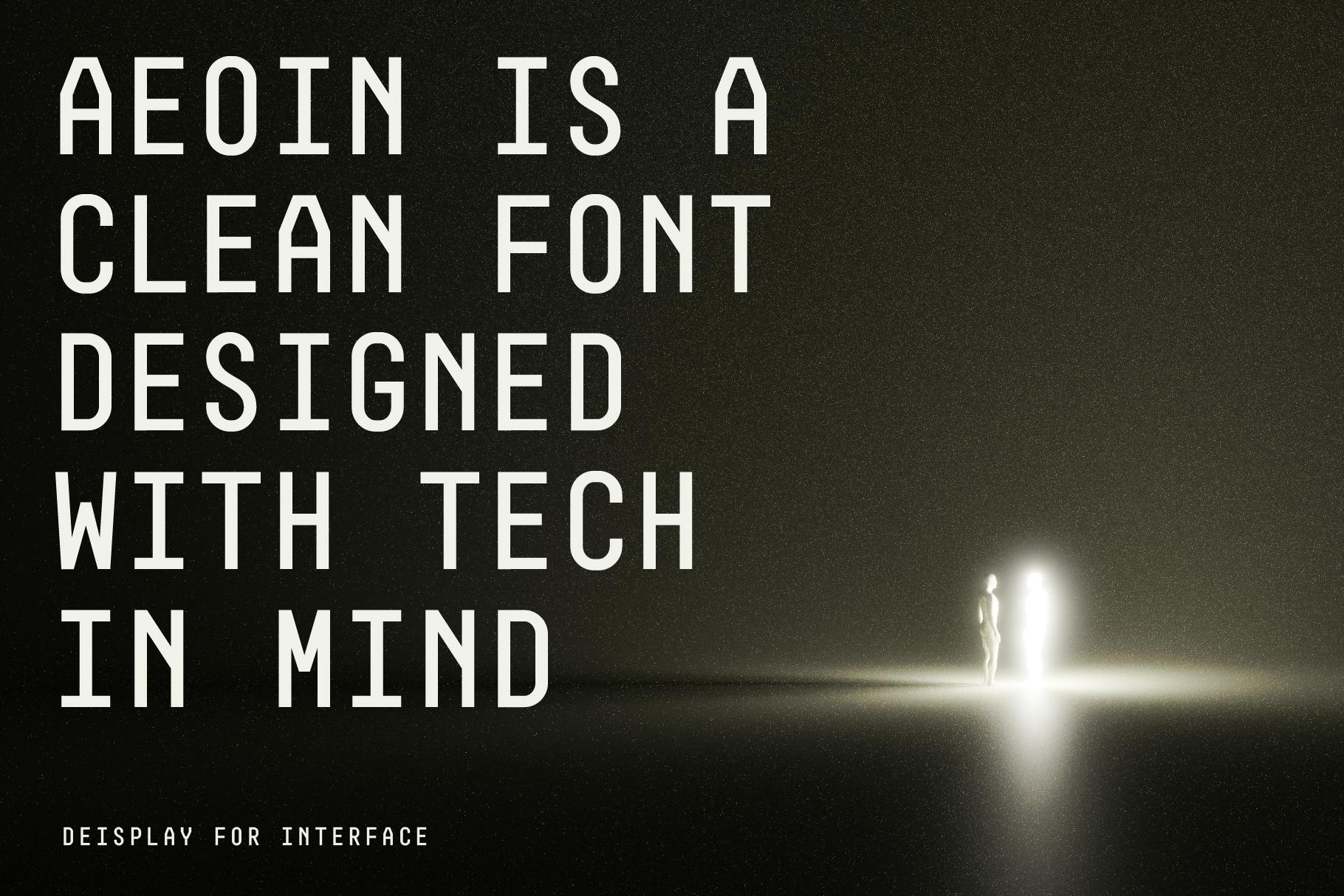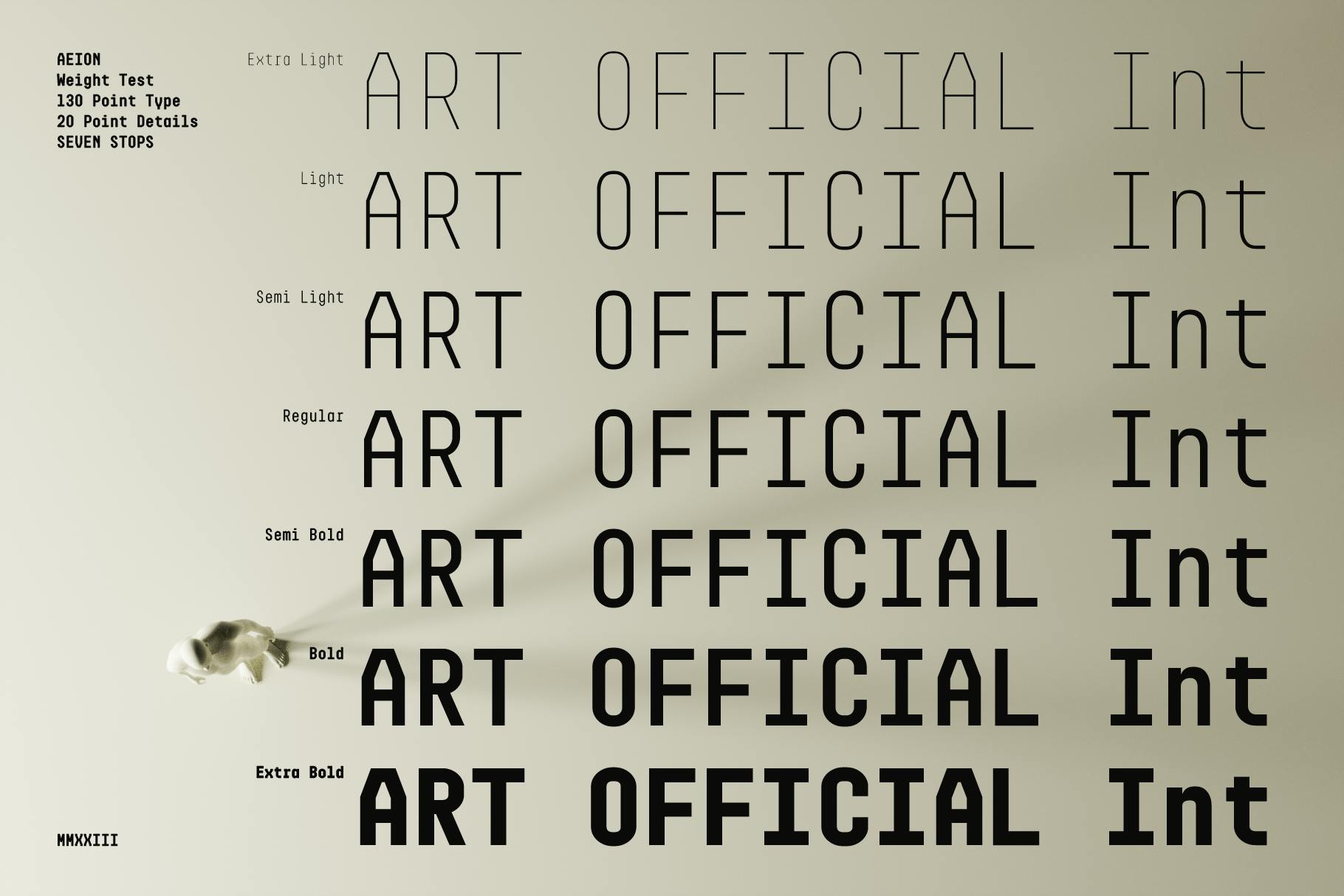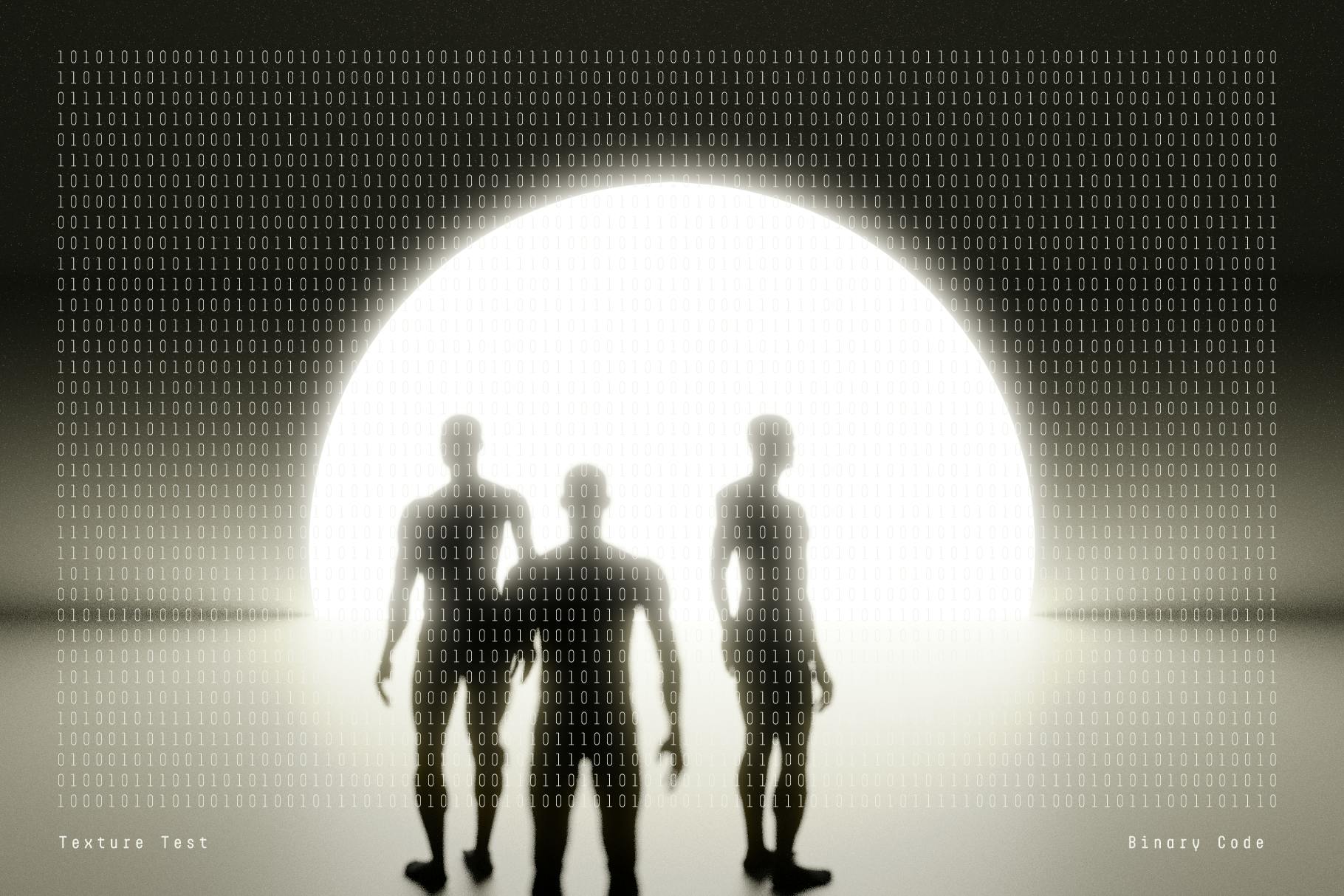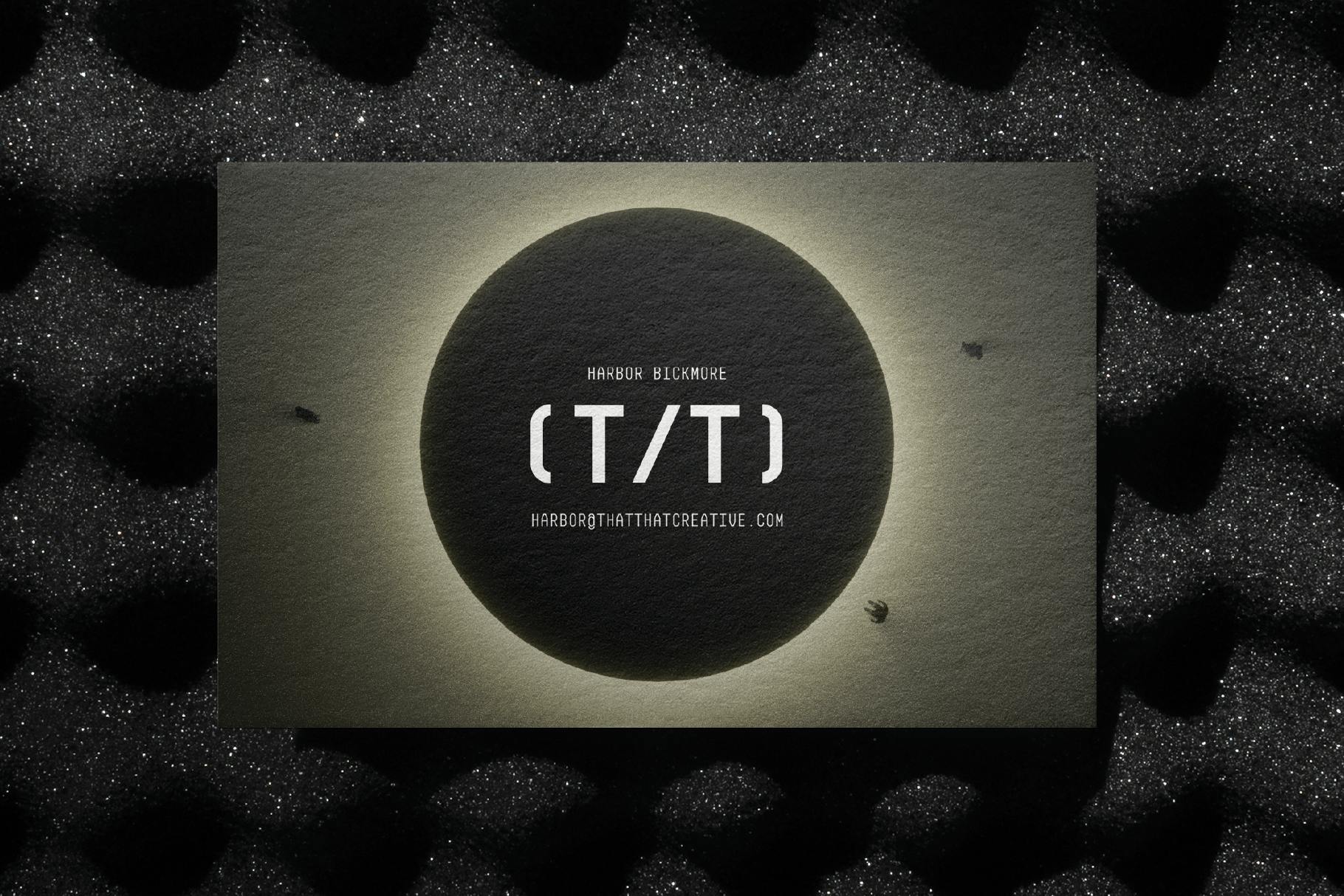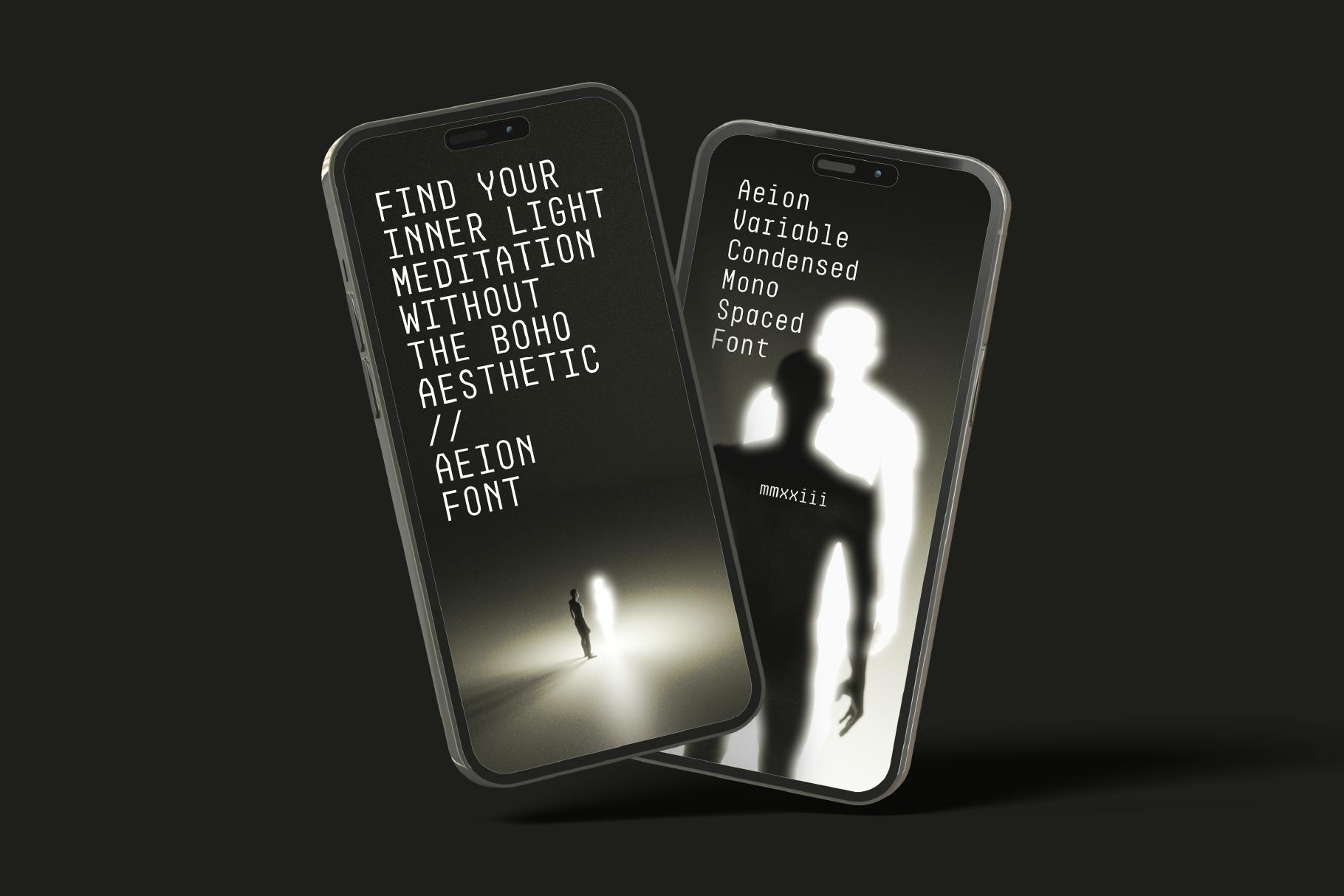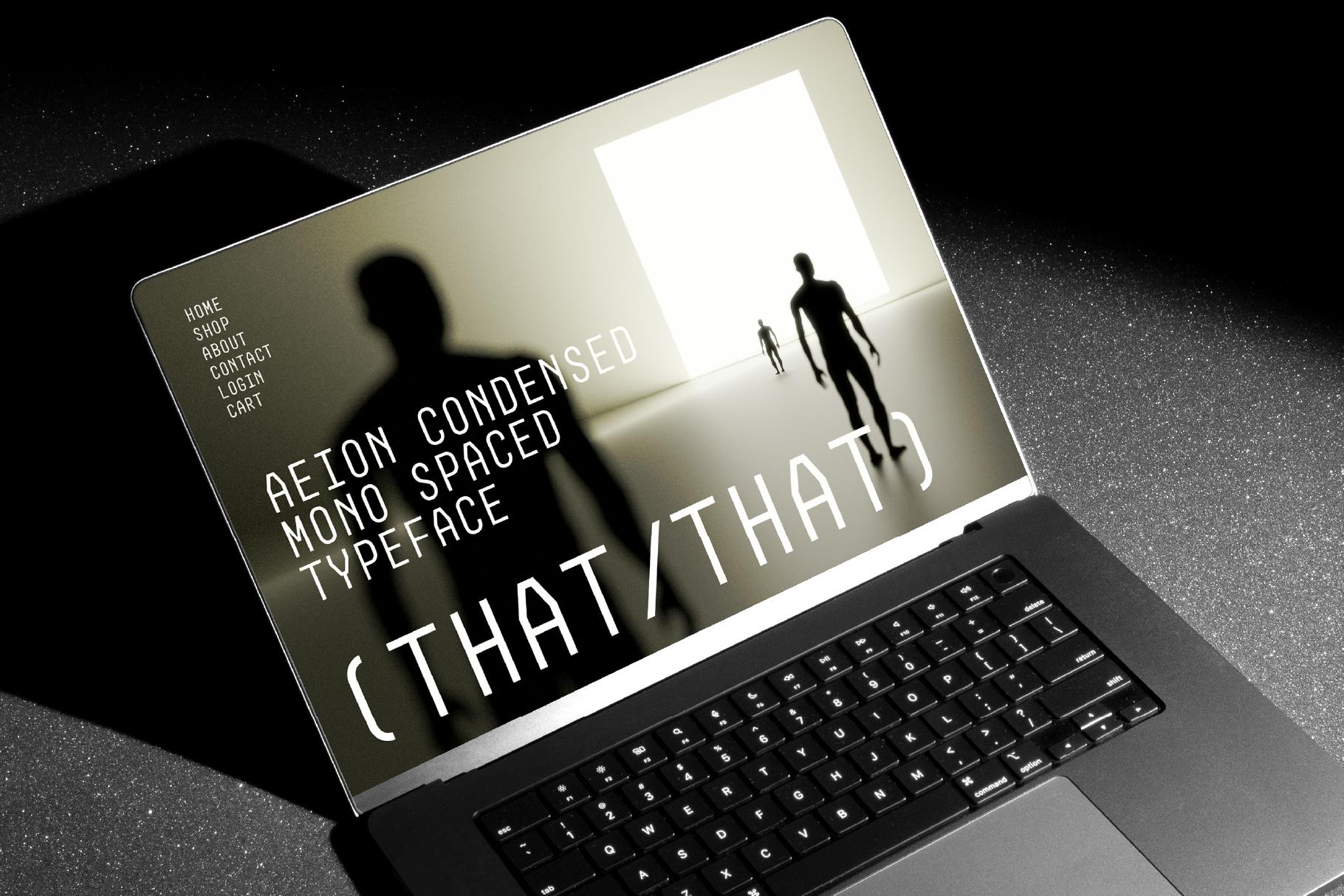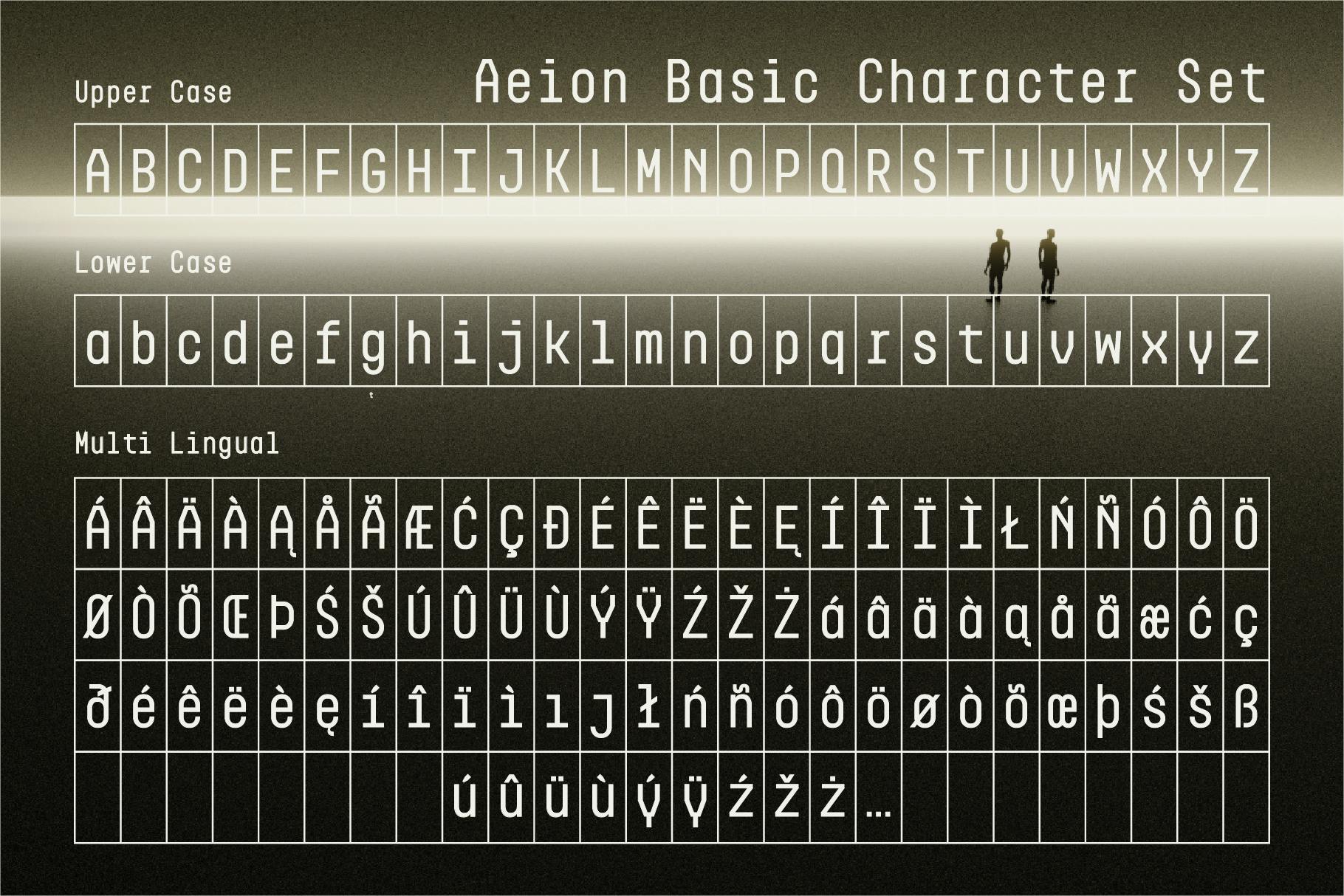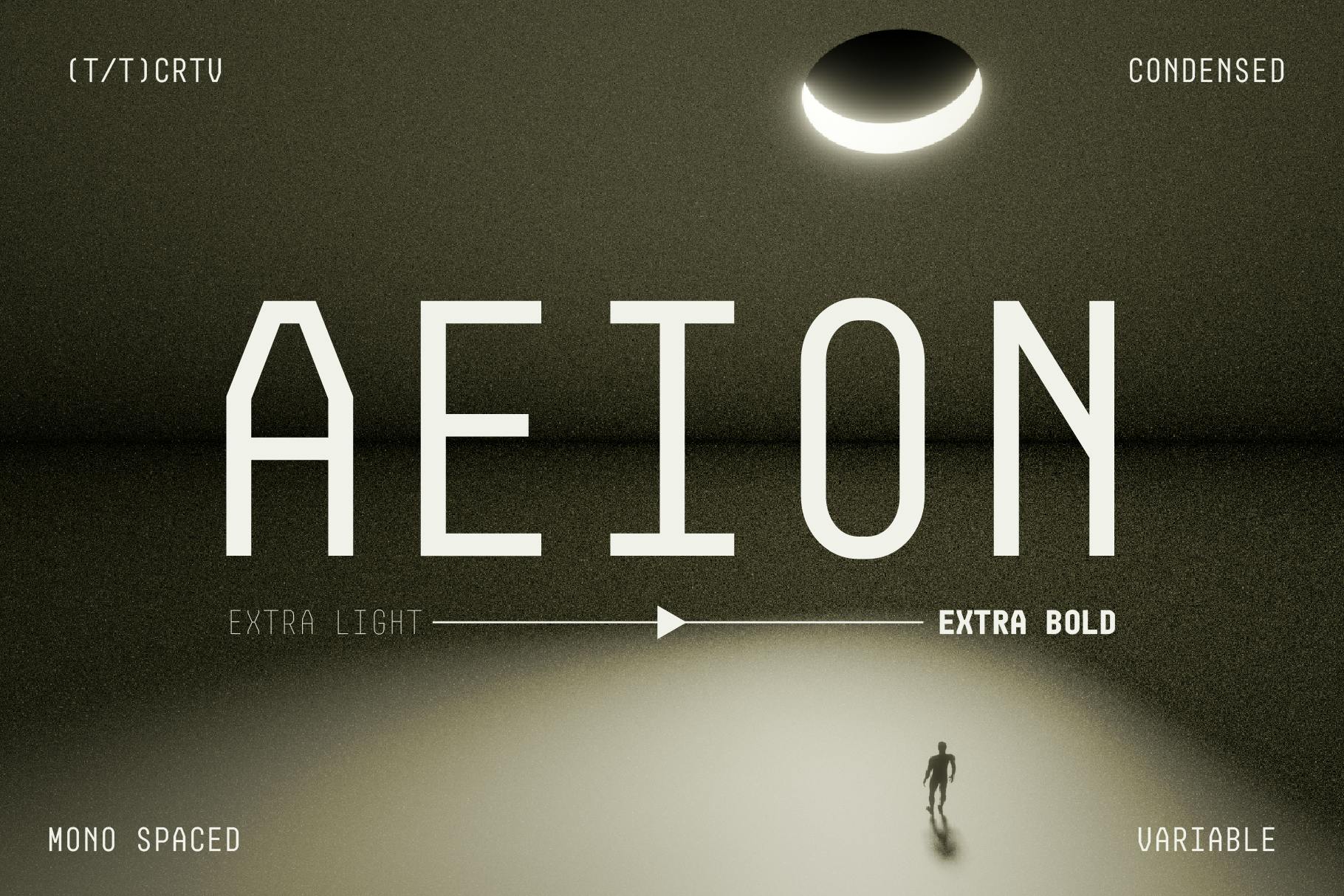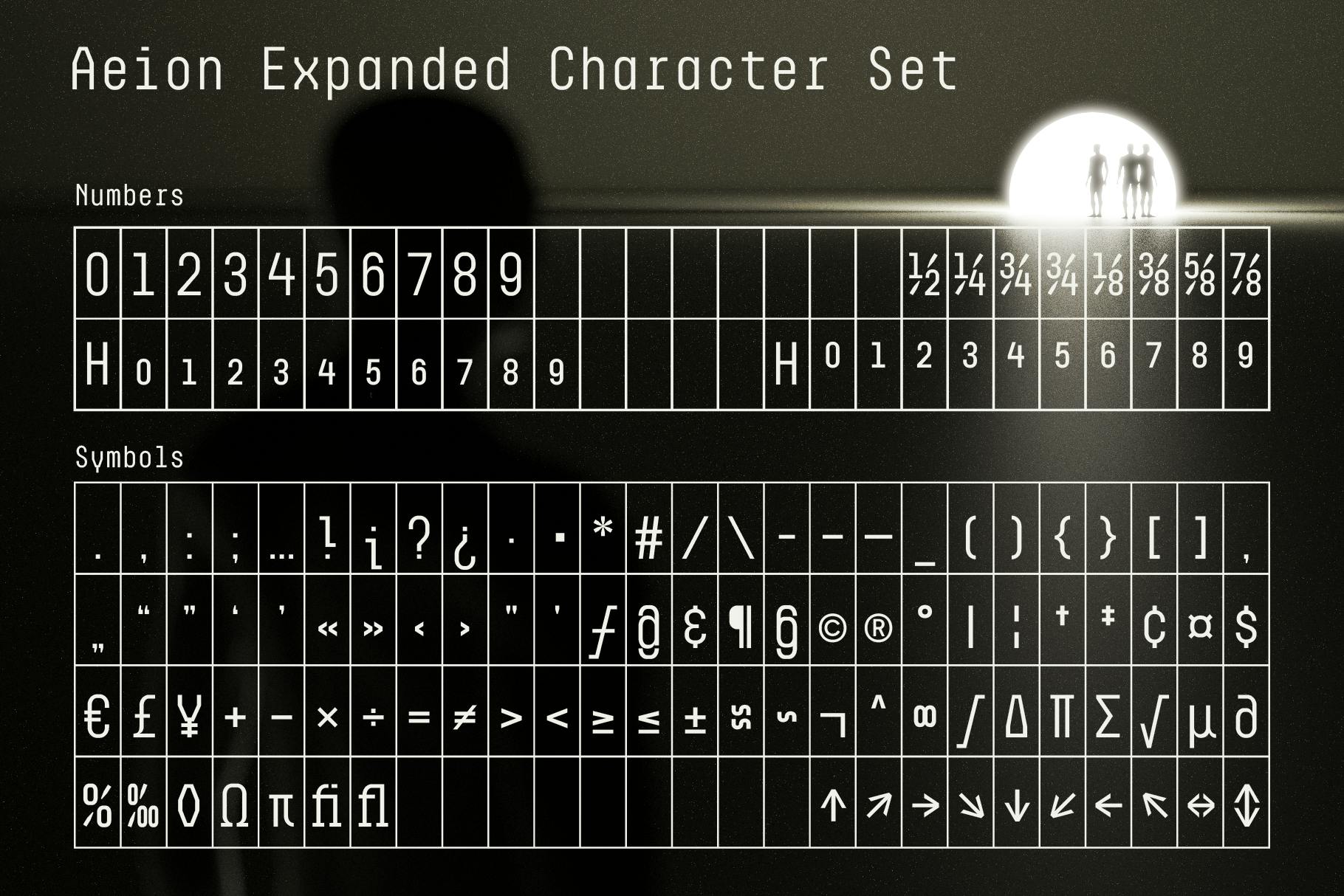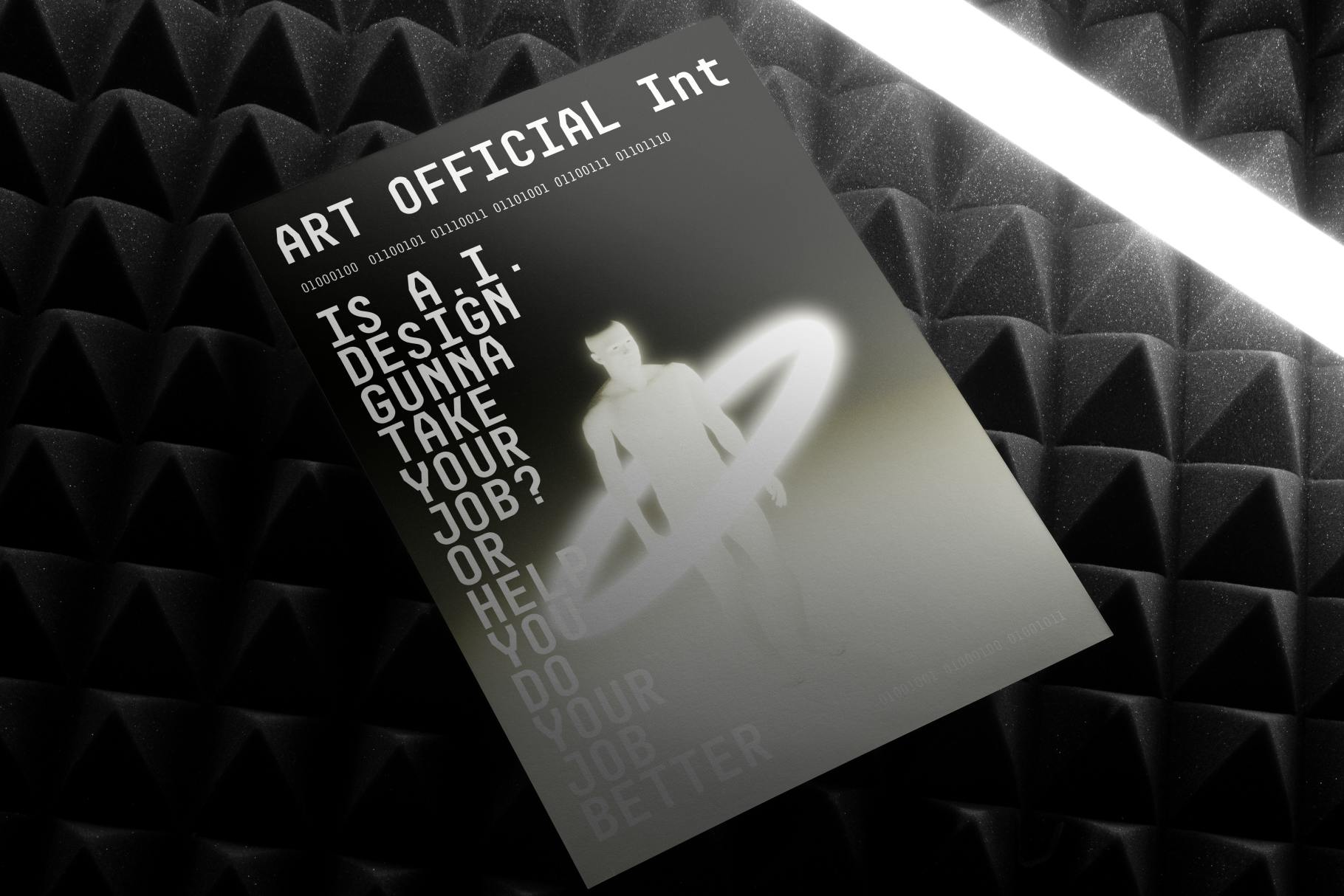
| فاصله گذاری | Monospace | Condensed |
فونت Aeion یک فونت مونو اسپیس فشرده است که در ۷ وزن و به صورت فونت متغیر ارائه میشود. این فونت با ذهنیت تکنولوژی طراحی شده است و انرژی جدی را منتقل میکند؛ به گونهای که شوخی کردن با آن دشوار است. فونت Aeion با حال و هوای مدرن و کمی نوستالژیک، برای هر پروژه معاصر مناسب است. اگر به تکنولوژی علاقه دارید، Aeion گزینهای عالی برای استفاده به عنوان فونت نمایش در پوسترها، برندینگ، شبکههای اجتماعی، مجلات، لوگوها و هر چیز دیگری است.